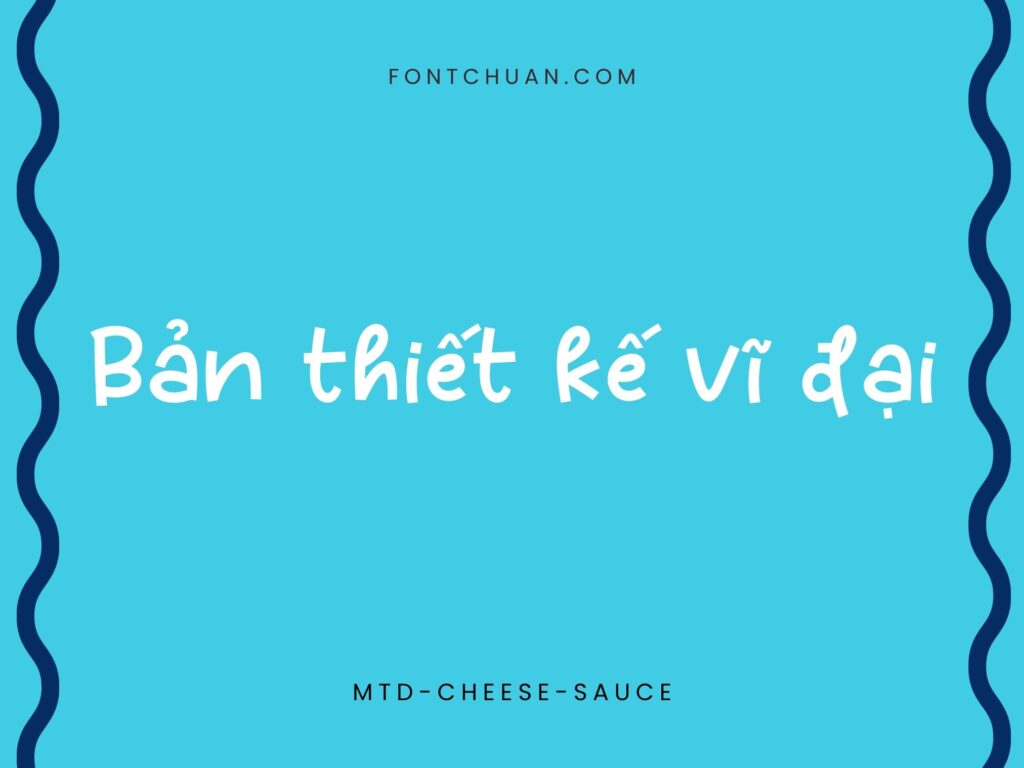
Font MTD Cheese Sauce là một kiểu chữ hiển thị vui nhộn, được thiết kế bởi Khurasan và đã được Việt hóa bởi Mộc Hạ. Font này hỗ trợ đầy đủ tiếng Việt cùng hơn 90 ngôn ngữ khác, mở rộng khả năng ứng dụng trong các thiết kế đa ngôn ngữ. Đây là một trong những phông chữ được cộng đồng thiết kế đánh giá cao và sử dụng trong nhiều dự án sáng tạo, đáp ứng nhu cầu đa dạng của người dùng.
MTD Cheese Sauce nổi bật với phong cách vui tươi và độc đáo, tạo cảm giác thân thiện và hấp dẫn. Font rất phù hợp cho các thiết kế logo, tiêu đề, bao bì sản phẩm, thiệp mời và các ấn phẩm đòi hỏi sự sáng tạo và nổi bật. Các ngành nghề phù hợp bao gồm quảng cáo, giáo dục và công nghệ. Font này cũng lý tưởng cho các sự kiện như Tết, Giáng sinh, Valentine và các lễ hội khác.